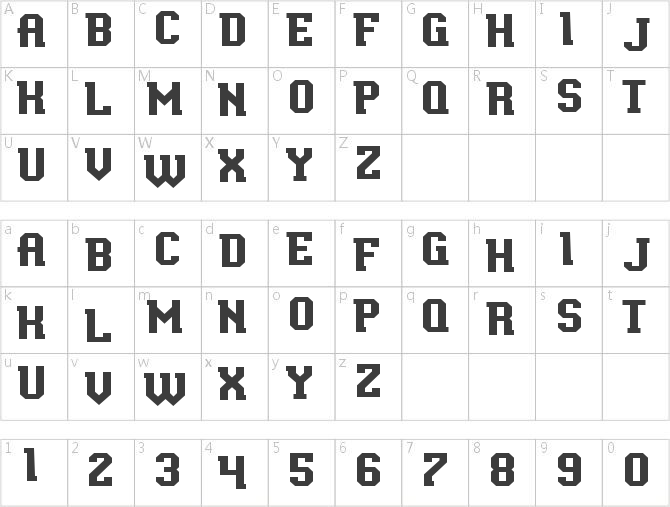
Baxter's Slab 詳情頁(yè)
Baxter's Slab字體字庫(kù)是一款讓人賞心悅目、百看不厭的英文字體,適合各類廣告和產(chǎn)品包裝設(shè)計(jì)應(yīng)用,字體大小0.02MB,格式為ttf字體,上傳用戶是素年錦時(shí),作者/版權(quán)方為未知